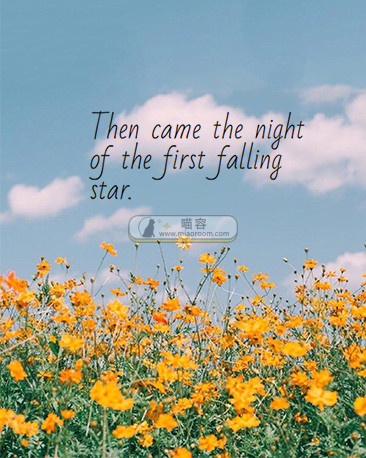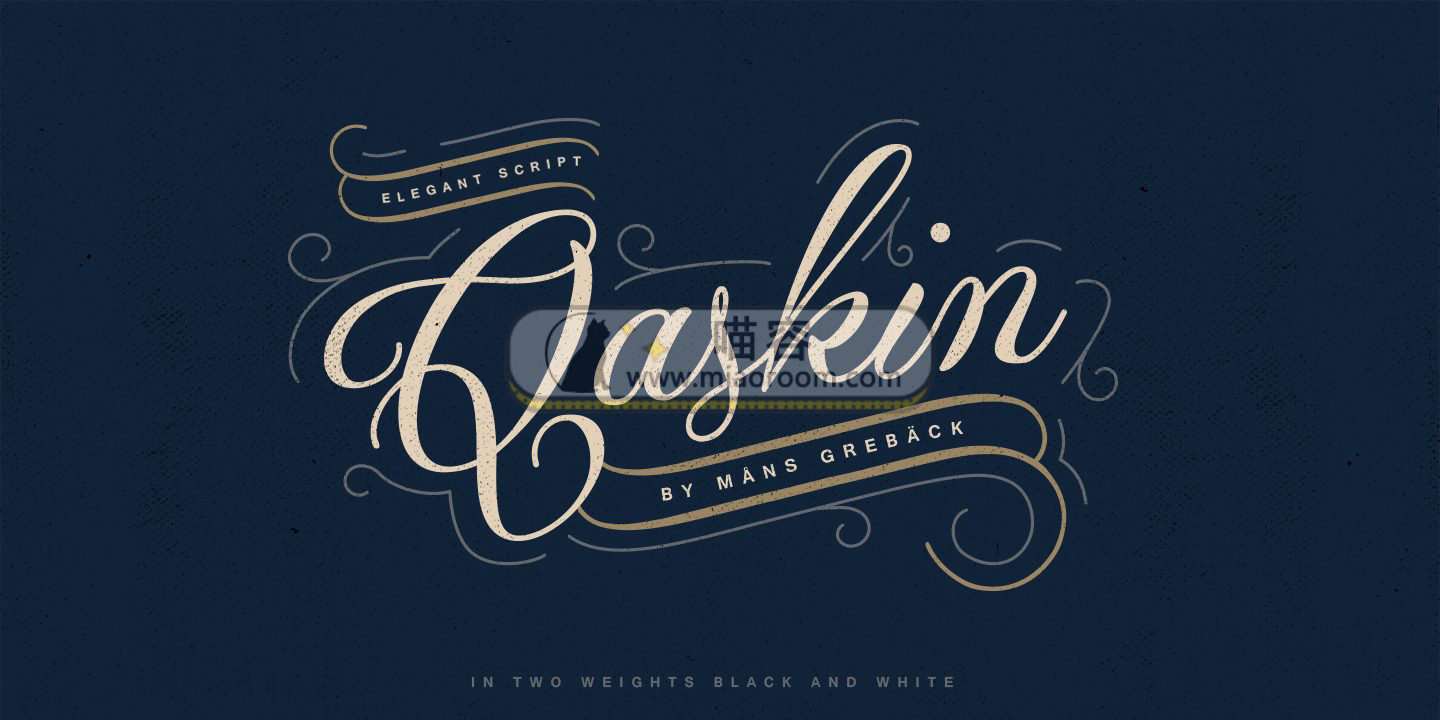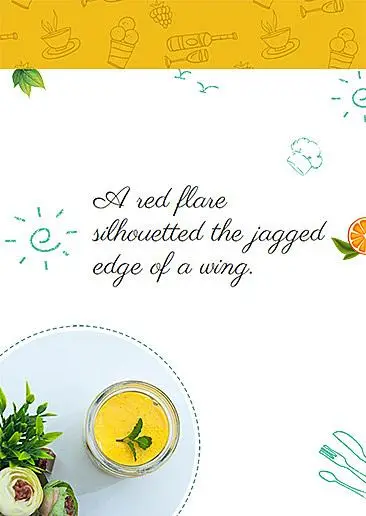
13種超好看的英文 手寫字體 (合集)
今天要分享13種英文手寫字體。這種字體我們會在海報,賀卡,卡片上經常看見。在一些好看的素材上用一種特別的字體有時候會給作品加分不少。
上面這些圖片是不是很出眾呢!如果你還是一個小白,在製作海報的時候感覺太單一了可以考慮一下換一種字體哦!
下面我來分享一下我今天帶來的13種字體~ 下面這些圖全是我自己隨意上網找的圖片然後加上相應的字體。是不是既可以小清新也可以唯美呢,真的是排版的好幫手哦!(*^__^*) 。趕緊動手下載起來把~~